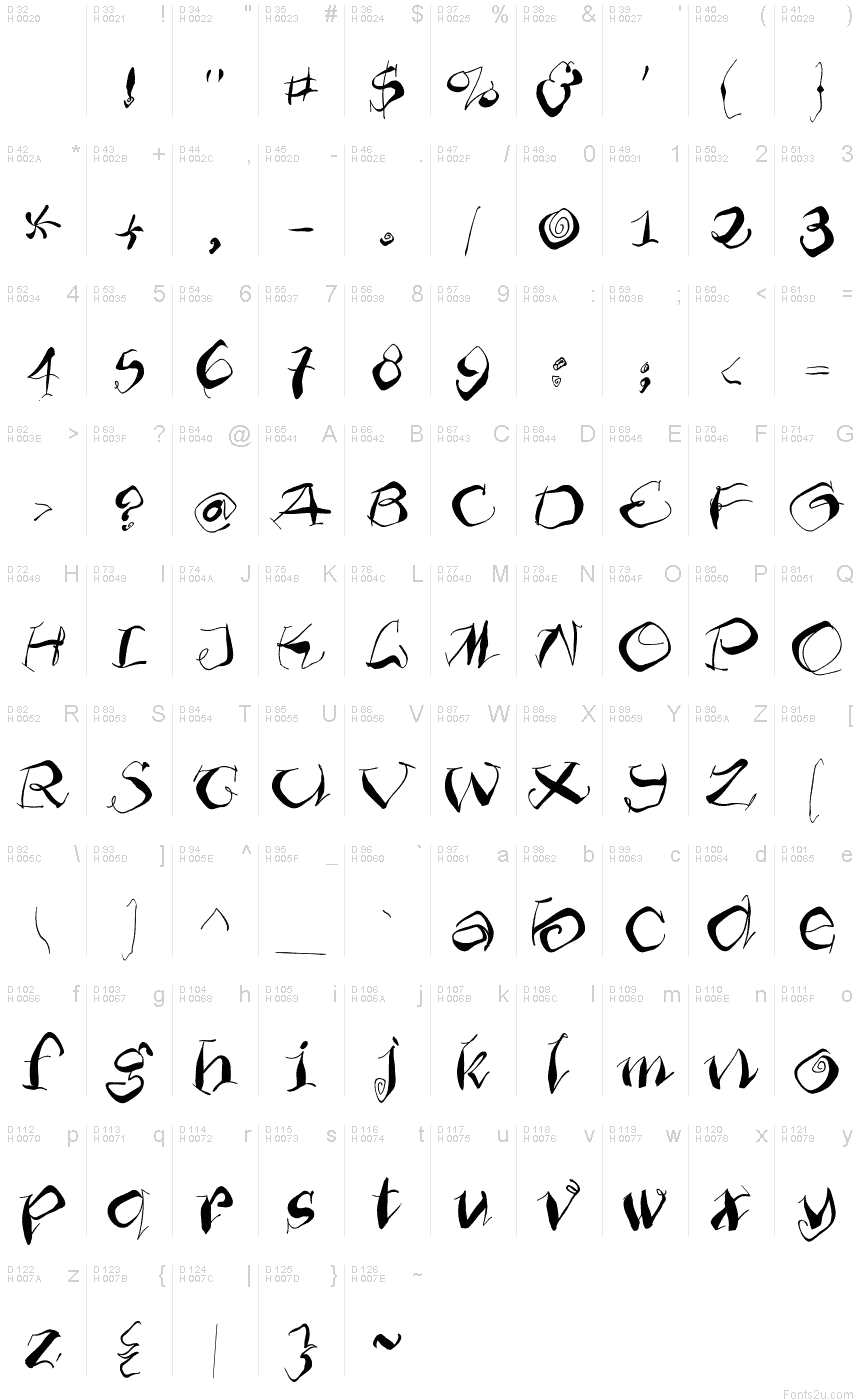
Furioso od M. Kleina to darmowy, dekoracyjny krój pisma typu display, który wygląda jak atrament porwany przez burzę: nabrzmiałe pociągnięcia, nerwowe zawijasy i nieoczekiwane skręty nadają każdemu słowu niespokojną, ręcznie rysowaną energię. Litery chwieją się i puchną, jakby zostały pospiesznie nabazgrane na szorstkim papierze, pozostawiając ciemne, atramentowe kształty z lekko drapieżnym pazurem. Jest chaotycznie, ale w większych rozmiarach projekt pozostaje czytelny, dzięki czemu ta dziwność sprawia wrażenie zamierzonej, a nie przypadkowej.
Dzięki Furioso nagłówki błyskawicznie zyskują nastrojowy, nietuzinkowy klimat, idealny do plakatów horrorów, eksperymentalnych zinów, okładek albumów, zaproszeń na Halloween, brandingu escape roomów i wyrazistych ulotek teatralnych. Ten darmowy font najlepiej sprawdza się, gdy dasz mu przestrzeń – ustaw go w dużym rozmiarze i połącz z prostym krojem bezszeryfowym w tekście głównym, aby dzikie krzywizny naprawdę mogły przykuć wzrok.